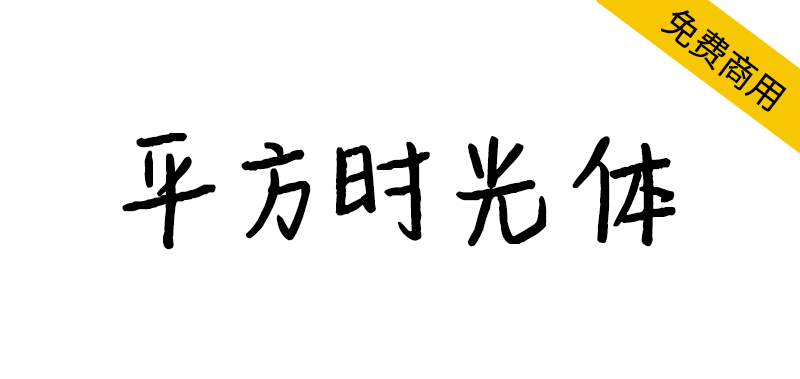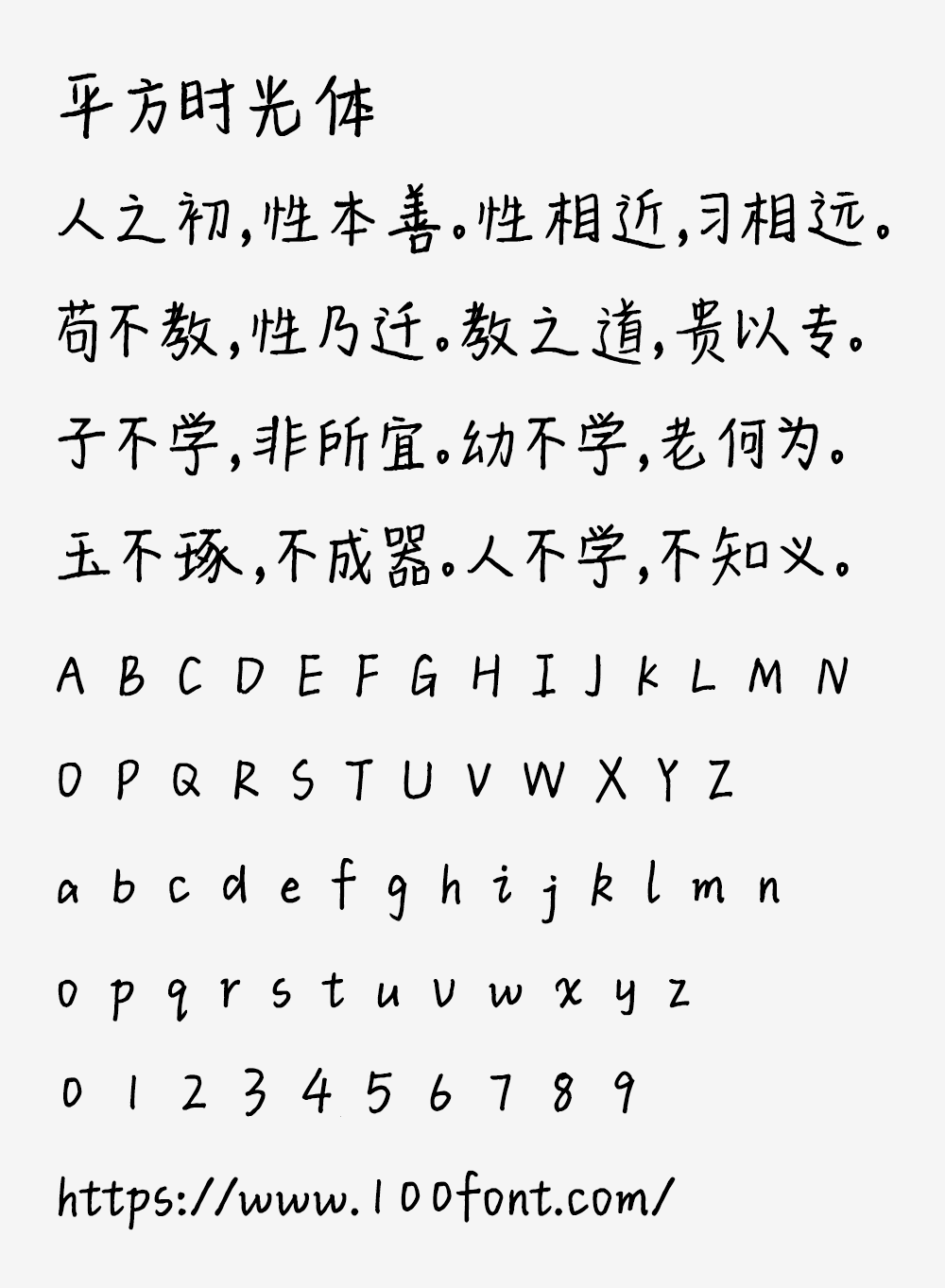
【平方时光体】一款充满文艺感的手写体字体
告别千篇一律的字体,迎接充满温度的书写感!这款“平方时光体”以其流畅自然的笔触和端庄秀丽的设计,瞬间提升作品的文艺气息。无论是个人手账还是商业海报,它都能完美驾驭。最关键的是,它对个人和企业完全免费,可放心用于任何商业项目,让你在创作时再无后顾之忧。
【平方时光体】一款充满文艺感的手写体字体
平方时光体是一款充满文艺气息的手写风格字体,其笔触流畅自然,线条细腻均匀,字形端庄秀丽,适合用于日记、信件、手账及海报等各类文艺设计场景。